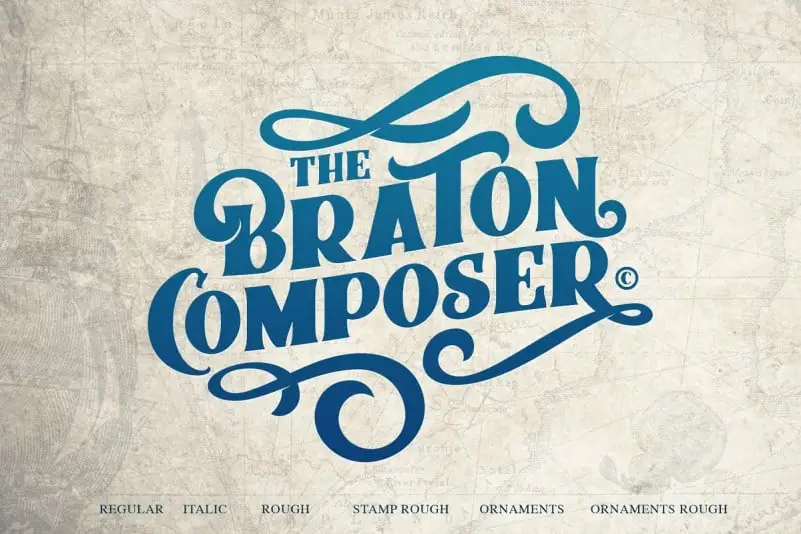
Braton Composer Bold Serif Font – Download Grátis
A fonte Braton Composer Bold Serif é uma criação do designer 99designs. Inspirada no alit design, ela transmite um estilo robusto e vintage com forte contraste, perfeitamente adaptado para projetos que desejam transmitir uma concepção firme e elegante. Ideal para identificarções de marca, headlines, ou qualquer projeto que valorize a sofisticação, Braton Composer é o tipo certo para estilos que buscam um ar tradicional e confiável. Suas linhas finas contrastando com as mais grossas criam uma aparência vibrante em design gráfico, garantindo que sua mensagem seja destacada no meio das páginas. Seja você designer ou editor de conteúdo, a Braton Composer será uma escolha estratégica para criar um layout impactante e sofisticado.